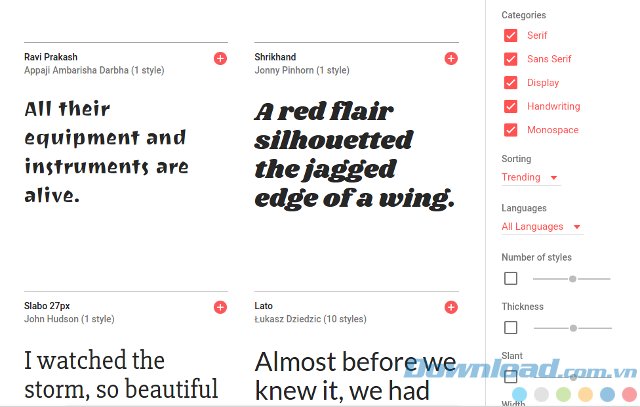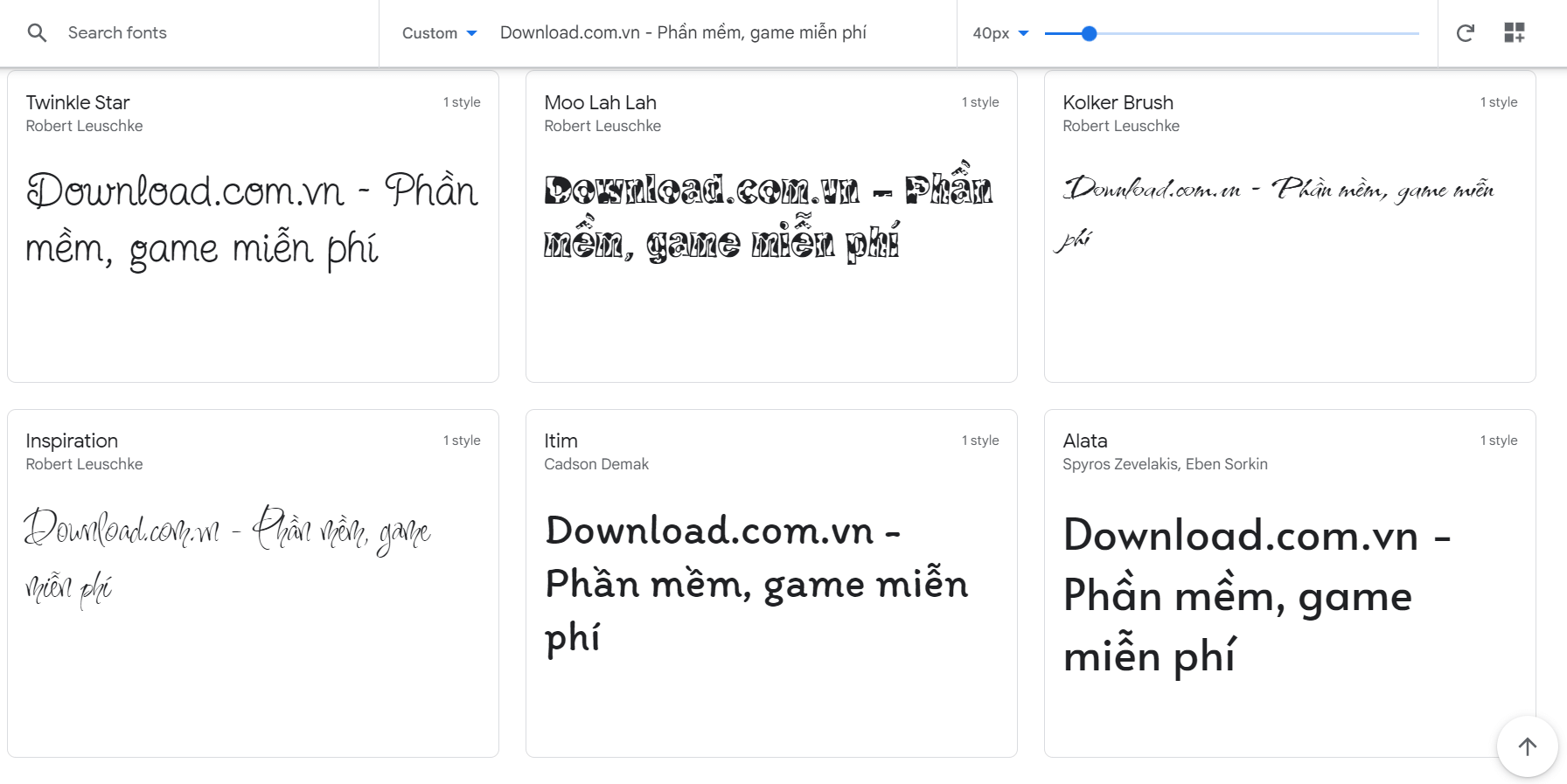
Trong thế giới thiết kế web hiện đại, phông chữ đóng vai trò quan trọng không kém gì hình ảnh hay bố cục. Một bộ phông chữ phù hợp có thể nâng tầm trải nghiệm người dùng, tạo nên sự chuyên nghiệp và thu hút cho website. Google Fonts, với kho tàng khổng lồ các phông chữ chất lượng cao và hoàn toàn miễn phí, đã trở thành lựa chọn hàng đầu cho các nhà thiết kế web trên toàn thế giới. Bài viết này sẽ đi sâu vào khám phá Google Fonts, những lợi ích của việc sử dụng nó và hướng dẫn cách tận dụng tối đa nguồn tài nguyên phong phú này.
Google Fonts là gì?
Google Fonts là một thư viện phông chữ mã nguồn mở, cung cấp hàng trăm phông chữ đa dạng về phong cách, ngôn ngữ và kiểu chữ. Toàn bộ phông chữ trong thư viện đều được cung cấp miễn phí và có thể được sử dụng trong các dự án cá nhân hoặc thương mại mà không cần lo lắng về vấn đề bản quyền. Điều này giúp tiết kiệm chi phí đáng kể so với việc mua các phông chữ thương mại. Hơn nữa, tính chất mã nguồn mở cho phép cộng đồng đóng góp và phát triển, liên tục bổ sung những phông chữ mới, đáp ứng nhu cầu đa dạng của người dùng.
Lợi ích của việc sử dụng Google Fonts:
Việc tích hợp Google Fonts vào quá trình thiết kế web mang lại rất nhiều lợi ích, bao gồm:
Đa dạng phong cách và ngôn ngữ: Google Fonts cung cấp một kho tàng khổng lồ các phông chữ với vô vàn phong cách khác nhau, từ cổ điển đến hiện đại, từ trang trọng đến thân thiện. Thư viện này còn hỗ trợ nhiều ngôn ngữ, bao gồm cả tiếng Việt, giúp bạn dễ dàng tìm được phông chữ phù hợp với nội dung và đối tượng khách hàng.
Tối ưu hóa hiệu suất: Google Fonts được tối ưu hóa để tải nhanh, đảm bảo tốc độ tải trang web không bị ảnh hưởng. Google sử dụng các công nghệ nén dữ liệu tiên tiến như WOFF 2.0 giúp giảm dung lượng file phông chữ, từ đó cải thiện tốc độ tải trang, đặc biệt hữu ích trên các kết nối mạng yếu. Hơn nữa, Google Fonts sử dụng hệ thống cache, giúp giảm thiểu thời gian tải lại phông chữ trên các trang web khác nhau sử dụng cùng một phông chữ.
Cập nhật thường xuyên: Google Fonts liên tục được cập nhật với những phông chữ mới và cải tiến, đảm bảo bạn luôn có những lựa chọn mới mẻ và hiện đại cho dự án của mình.
Thông tin minh bạch: Mỗi phông chữ trên Google Fonts đều có thông tin chi tiết về tác giả, giấy phép sử dụng và các thông số kỹ thuật, giúp bạn có cái nhìn tổng quan và lựa chọn phông chữ phù hợp một cách dễ dàng.
-
Sao chép mã nhúng: Sau khi chọn xong các phông chữ, Google Fonts sẽ cung cấp cho bạn một đoạn mã nhúng. Sao chép đoạn mã này.
-
Nhúng mã vào trang web: Thêm đoạn mã đã sao chép vào phần
<head>của trang web HTML của bạn. Đoạn mã này sẽ liên kết trang web của bạn với Google Fonts và tải các phông chữ đã chọn. -
Sử dụng phông chữ trong CSS: Cuối cùng, sử dụng tên phông chữ đã chọn trong CSS để áp dụng cho các phần tử trên trang web của bạn. Ví dụ:
font-family: 'Roboto', sans-serif;
Tóm lại:
Google Fonts là một nguồn tài nguyên vô cùng quý giá cho các nhà thiết kế web. Với kho tàng phông chữ đa dạng, chất lượng cao, miễn phí và dễ dàng sử dụng, Google Fonts giúp đơn giản hóa quá trình thiết kế, tiết kiệm thời gian và chi phí, đồng thời nâng cao tính thẩm mỹ và trải nghiệm người dùng cho website. Hãy tận dụng tối đa nguồn tài nguyên này để tạo nên những website đẹp mắt và chuyên nghiệp.
Danh sách một số phông chữ phổ biến trong Google Fonts (một phần danh sách đã được cung cấp):
(Lưu ý: Đây chỉ là một phần nhỏ trong số hàng trăm phông chữ có sẵn trên Google Fonts. Danh sách đầy đủ có thể được tìm thấy trên trang web chính thức.)
- Roboto: Phông chữ sans-serif phổ biến, hiện đại và dễ đọc.
- Open Sans: Sans-serif khác, dễ đọc và đa năng.
- Lato: Sans-serif thanh lịch và hiện đại.
- Montserrat: Sans-serif mạnh mẽ và hiện đại.
- Playfair Display: Serif trang trọng và sang trọng.
- Merriweather: Serif cổ điển, dễ đọc.
- Oswald: Sans-serif đậm và dễ nhìn.
- Raleway: Sans-serif linh hoạt, phù hợp với nhiều mục đích.
- Poppins: Sans-serif hiện đại và thanh lịch.
- Và nhiều phông chữ khác với nhiều kiểu dáng, phong cách khác nhau.